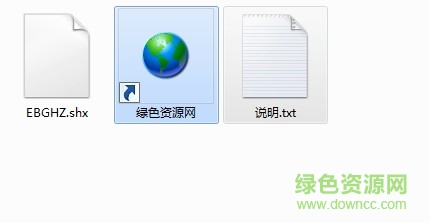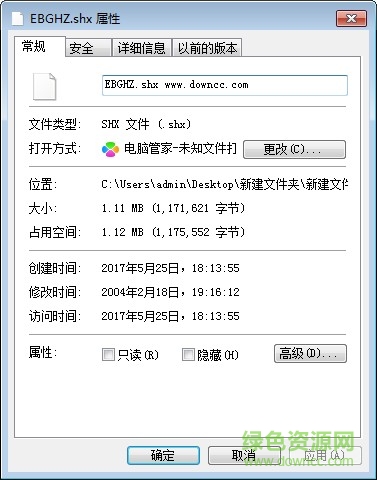
ebghz.shx字體
ebghz.shx字體是一款cad軟件的常用字體,使用cad工作學(xué)習(xí)的朋友們經(jīng)常使用,如果缺少了它,在cad中有些字體就無法顯示了,小編為大家?guī)砻赓M下載地址。歡迎大家來綠色資源網(wǎng)踴躍下載哦!
ebghz.shx字體簡介:
ebghz也是CAD常用字體之一,小編在繪圖的時候經(jīng)常打開圖紙會提示缺少ebghz字體,而且網(wǎng)上極少提供這種字體下載,小編現(xiàn)在把該字體分享給大家,其實這個字體主要是解決特殊符號的比如“一級鋼筋符號、二級鋼筋符合、三級鋼筋符號、預(yù)應(yīng)力鋼筋符號、文字上標(biāo)、及下標(biāo)”。使用的效果還是非常好的,不常用的字體,網(wǎng)上也比較難找到,請大家好好珍惜吧